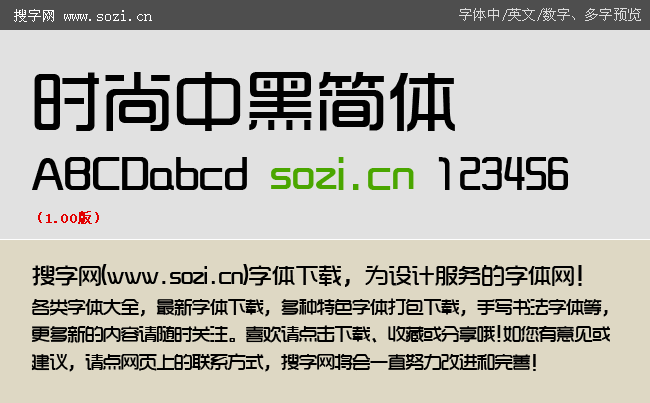
時尚中黑簡體
搜字網(wǎng)提供一款時尚中黑簡體字體下載,該字體由時尚傳媒集團(tuán)自主設(shè)計,是國內(nèi)首家以企業(yè)名稱命名的規(guī)范字體,時尚中黑字體整體字形筆畫均衡,風(fēng)格現(xiàn)代,字體方中帶圓,端莊雅致,簡約時尚。適宜用于時尚類企業(yè)形象、產(chǎn)品名稱和廣告標(biāo)題類用字。